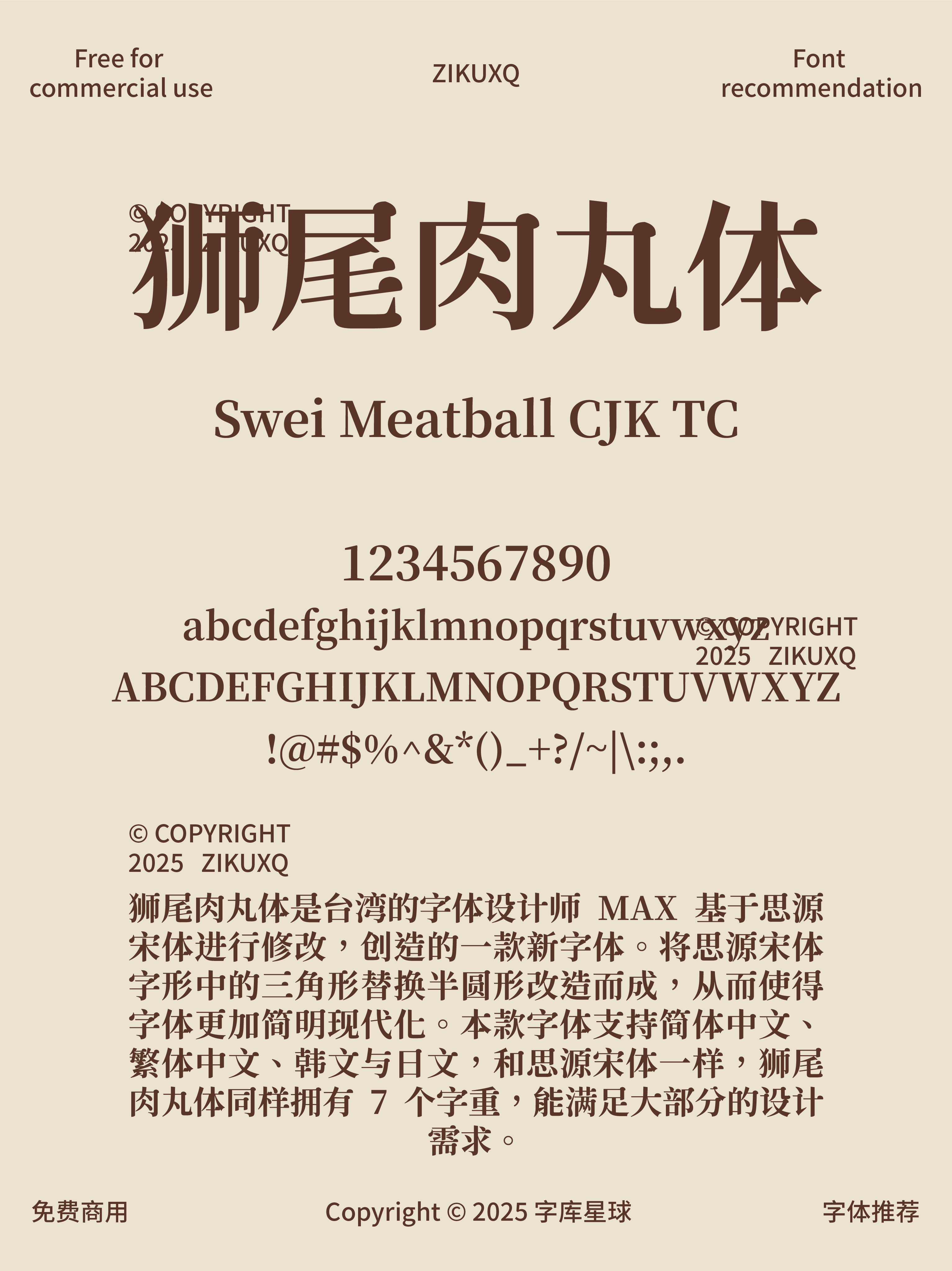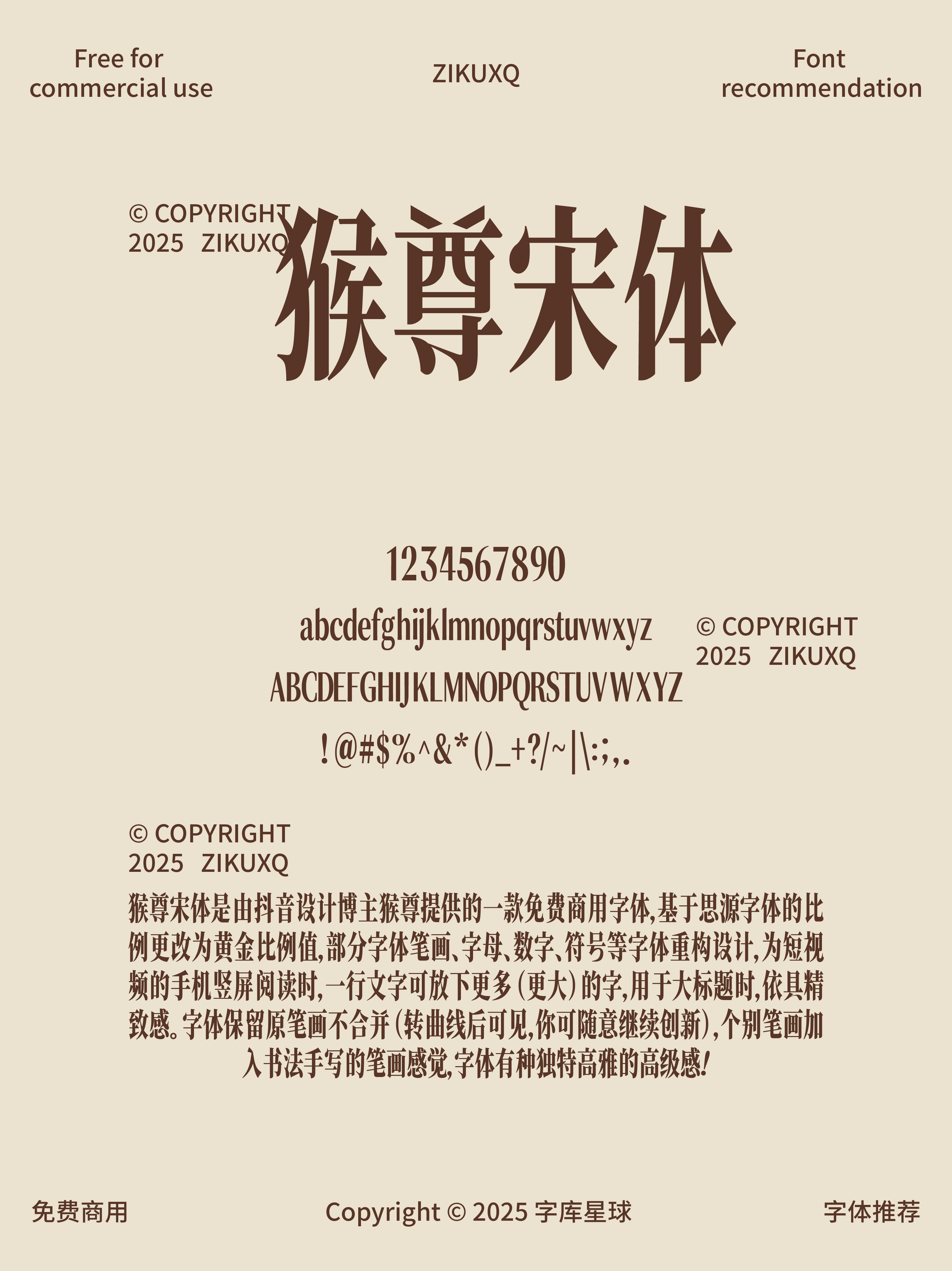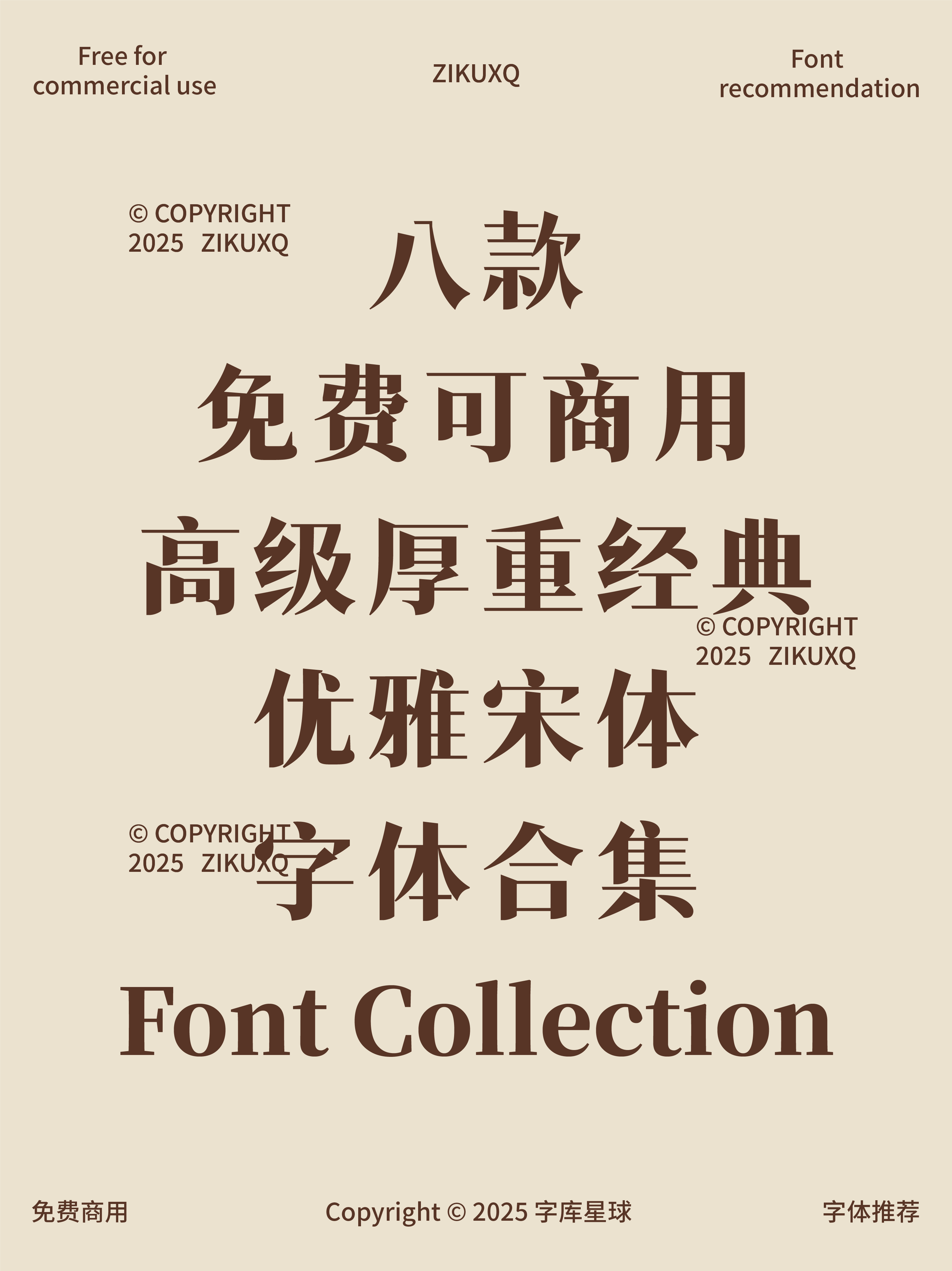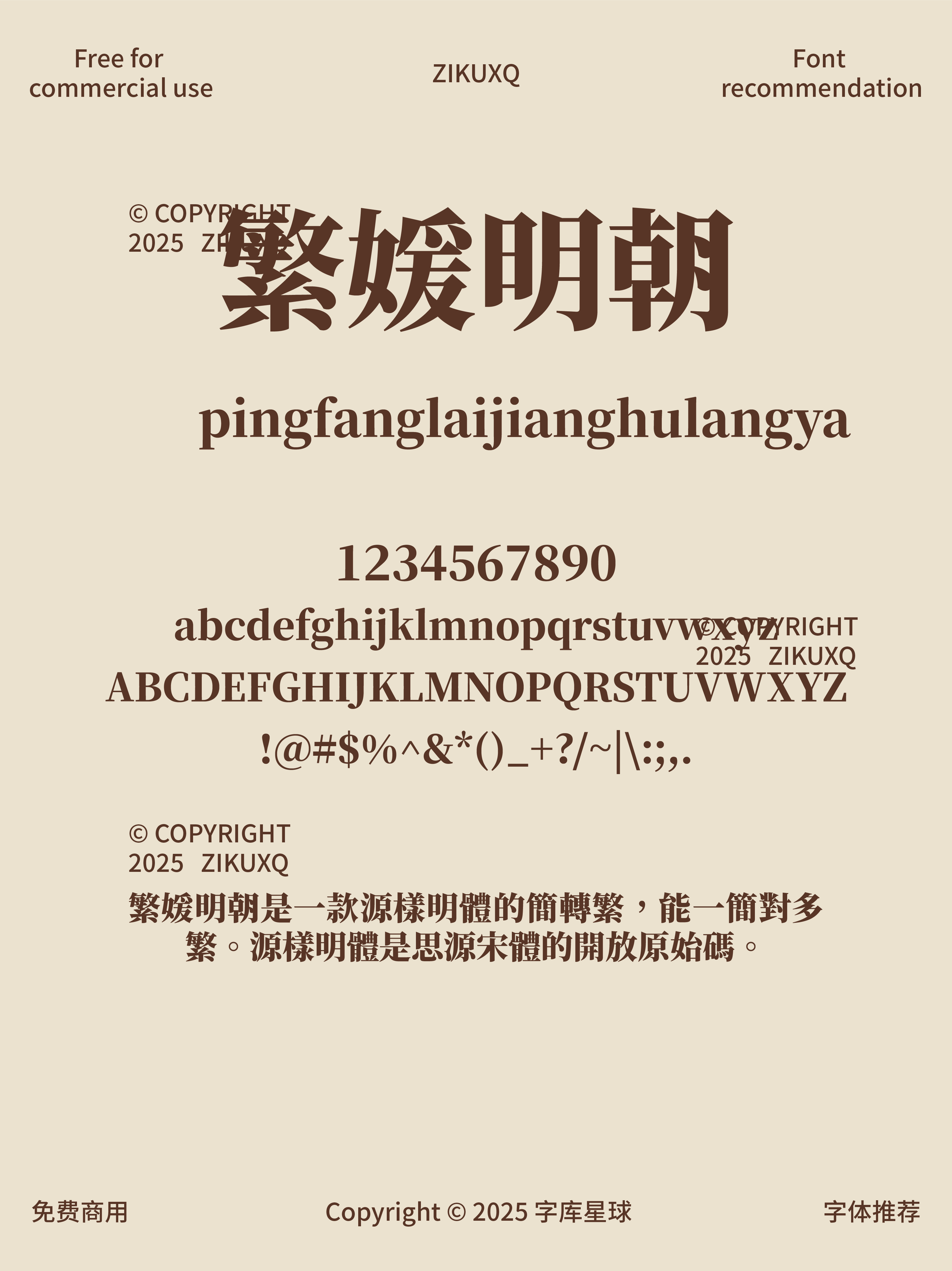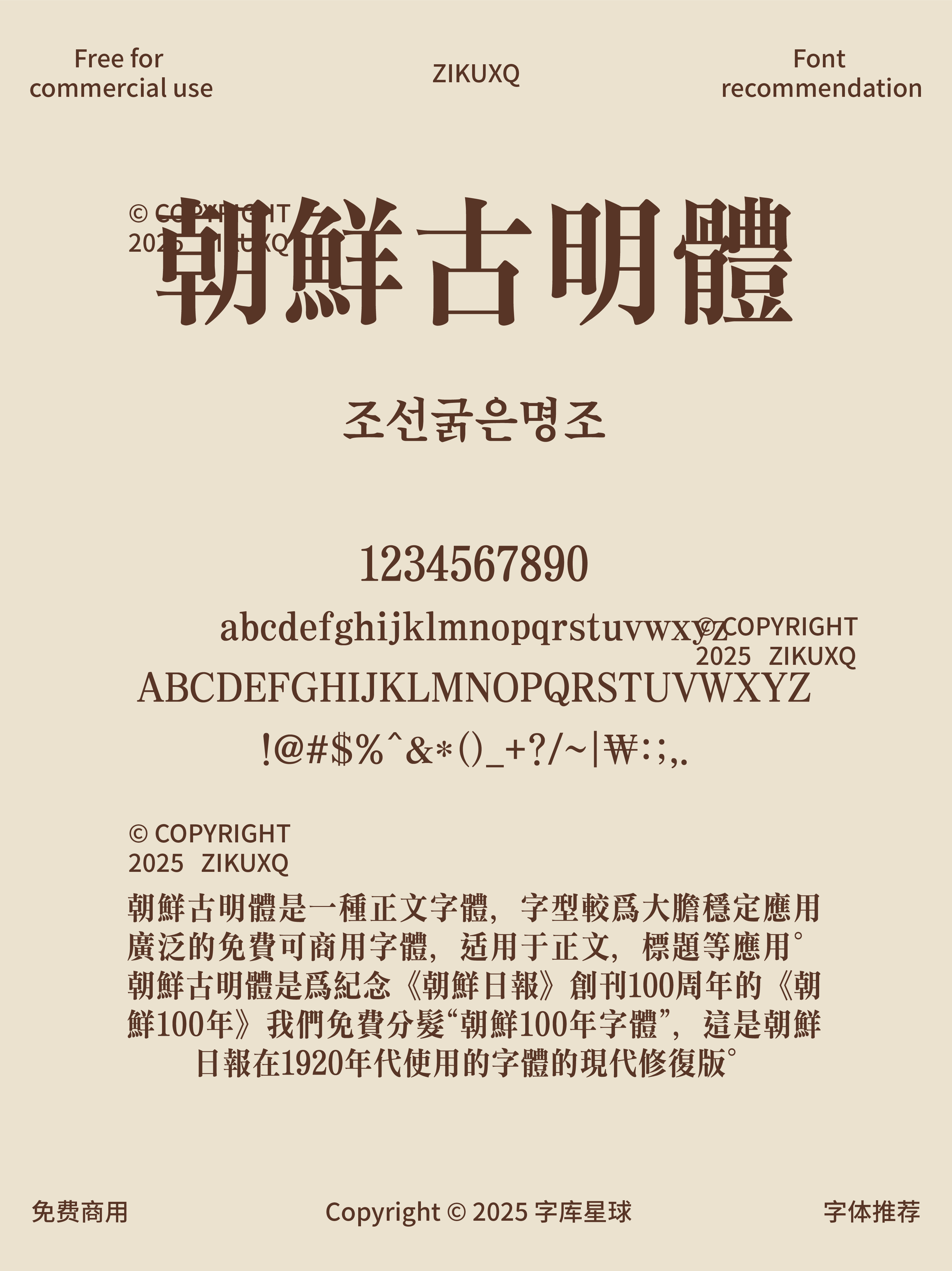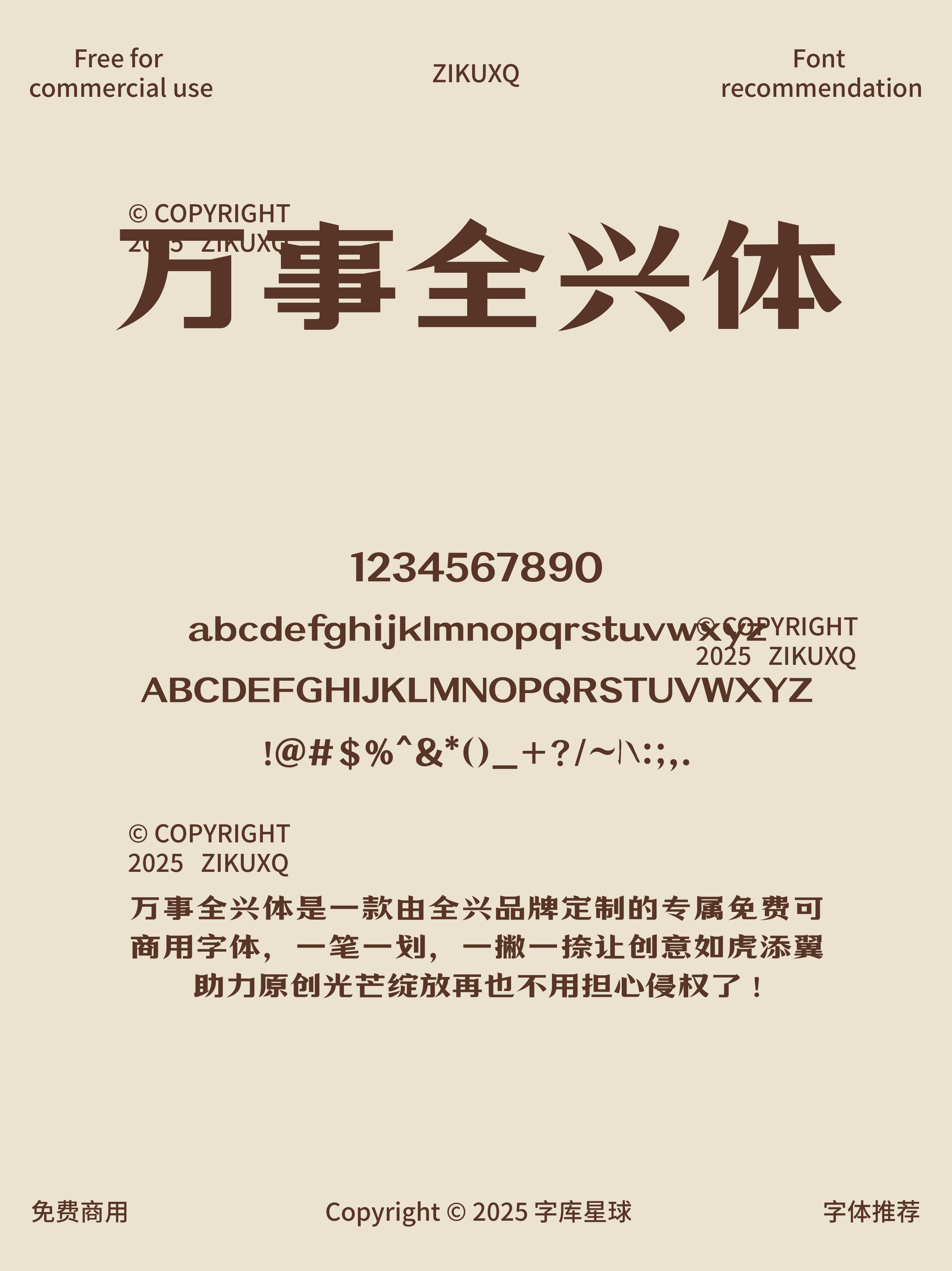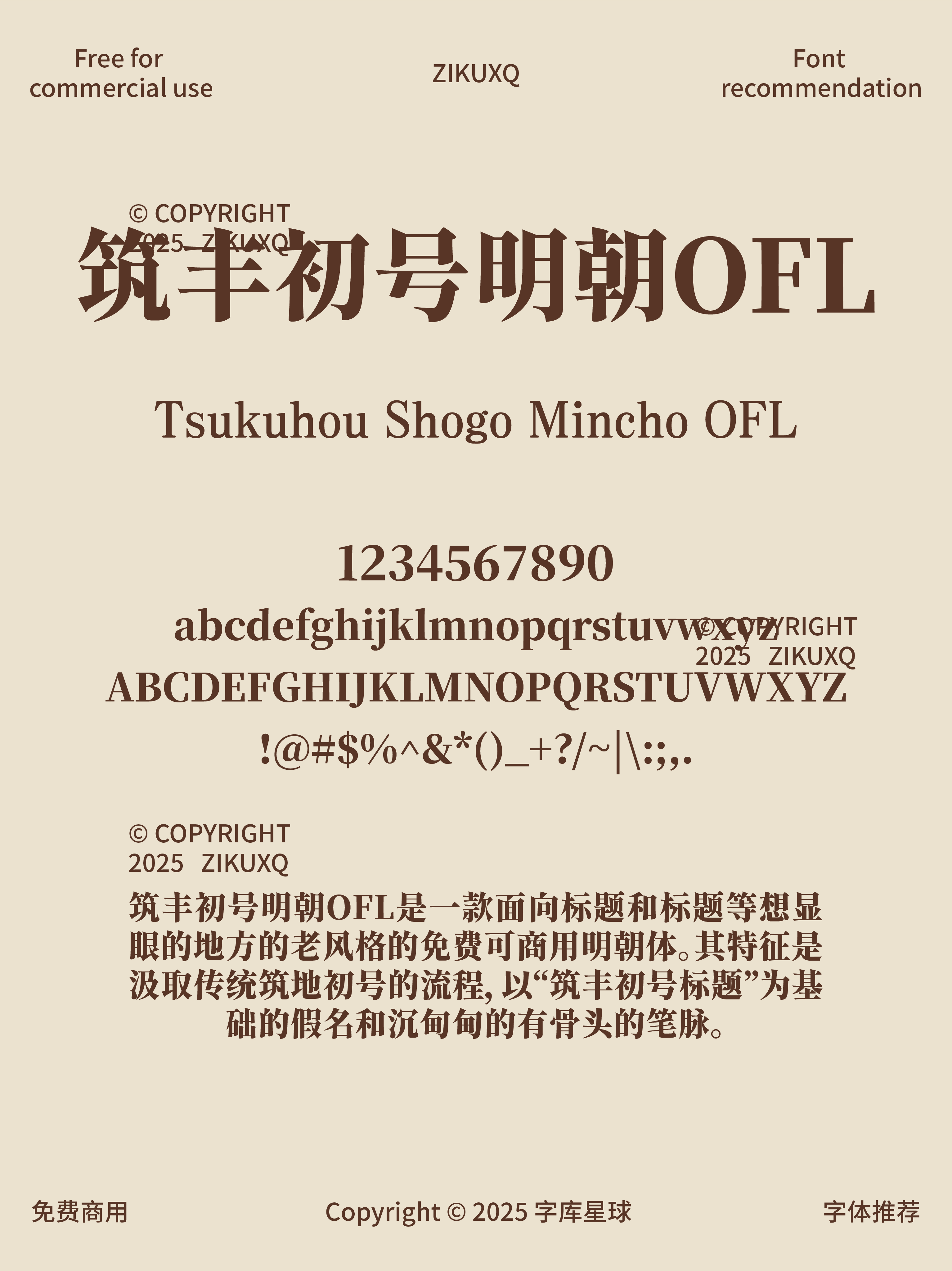
八款免费可商用高级厚重经典优雅宋体
今天给大家分享八款超绝的免费可商用高级宋体,每一款都有着独特的魅力~
字体笔画粗壮有力,整体风格非常大气,有一种蓬勃向上的精气神,用于品牌标题设计,能瞬间抓住人们的眼球。
笔画间有着独特的韵味,结构严谨又不失灵动,给人一种稳重大气又亲切的感觉,无论是正文还是标题都很适配。
这些宋体各有千秋,无论是海报设计、书籍排版、网页设计还是品牌 logo 设计等场景,都能大放异彩,关键还免费可商用,宝子们赶紧收藏起来,说不定哪天就用到啦~